15 fonts gratis para Photoshop: mejora tus piezas digitales
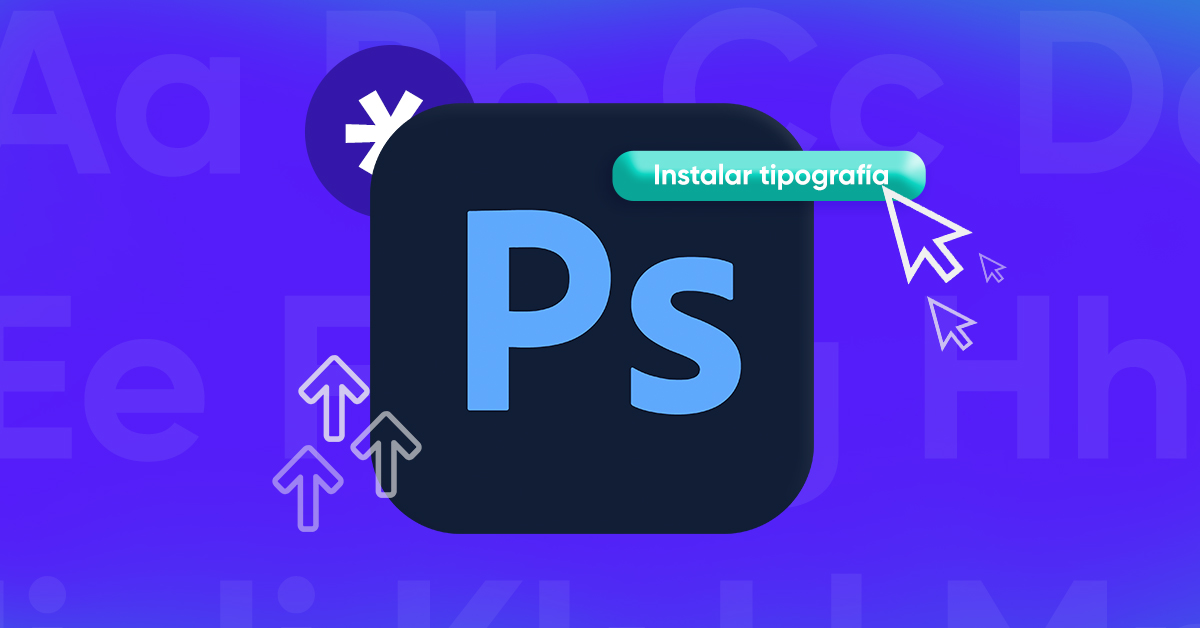
¿Te gustaría tener más opciones que las clásicas fonts para Photoshop?
Desde que instalas Photoshop, el software incluye una gran variedad de tipografías que te servirán mucho para la creación de tus textos.
Puedes encontrar las fonts de Adobe, algunas más actualizadas o también puedes encontrar las que son del clan “Comic Sans” que muy pocos diseñadores usan y por esa misma razón, en esta nota te ofrecemos una lista con 15 fonts para Photoshop gratis y otros recursos más que te ayudarán en el diseño de tus piezas gráficas.
Adobe Fonts: Fuentes gratis para Photoshop 2021
Puedes utilizar Adobe Fonts para agregar nuevas y únicas fuentes tipográficas para Photoshop, así como también para otros softwares de diseño como Illustrator, InDesign y más.
Viksi
Viksi es una fuente para Photoshop de escritura moderna, limpia y profesional.
Puedes usarla en anuncios publicitarios, creación de logotipos o en cualquier diseño que necesite una font elegante y clásica.